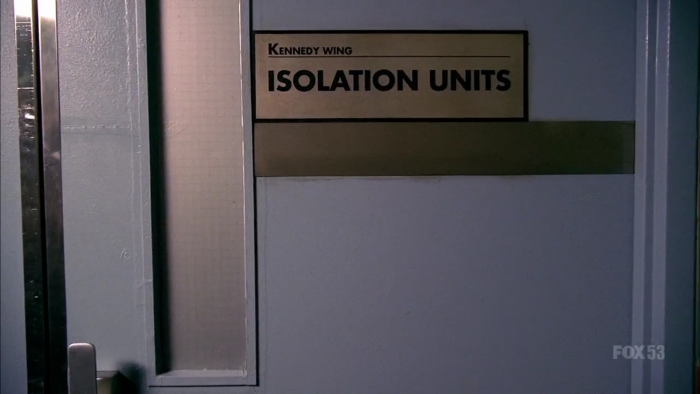
Schrift im Hospital (Film)
Im ersten Teil der Serie "Fringe" ist mir das Schild im angehängten Screenshot aufgefallen.
Hat jemand eine Idee, welche Schrift dafür verwendet wurde? Die Kombination "LA" sieht arg eng gesetzt aus.